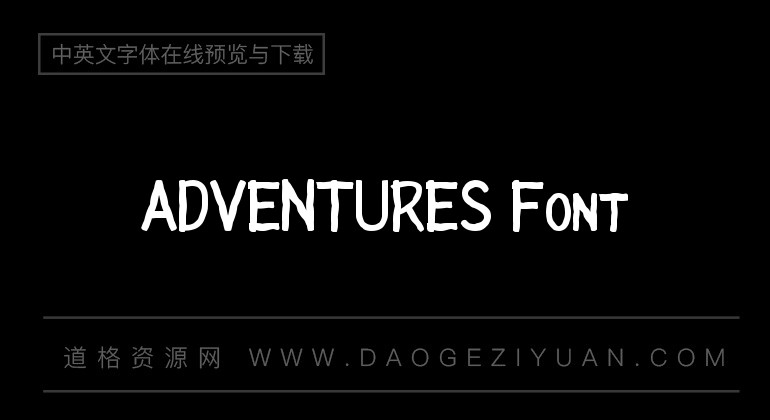
ADVENTURES Font 字体是一种粗犷、有力、自信的字体,用于强调和突出文字。它的设计灵感来自于野外探险和户外旅行时常见的标志和标识。字体的特点包括粗实的线条和角度,几何形状和弯曲的弧线。这些设计元素使 ADVENTURES Font 字体看起来非常现代和时尚,适合于户外运动、旅游、探险、摄影和其他大胆冒险主题的品牌标识、广告和包装等场合。内容介绍
ADVENTURES Font是一款非常不错的手写艺术字体,具有很好的视觉感,适合于文化类的宣传设计、商业类品牌的广告和产品包装设计以及个性化文字排版等较多场景。